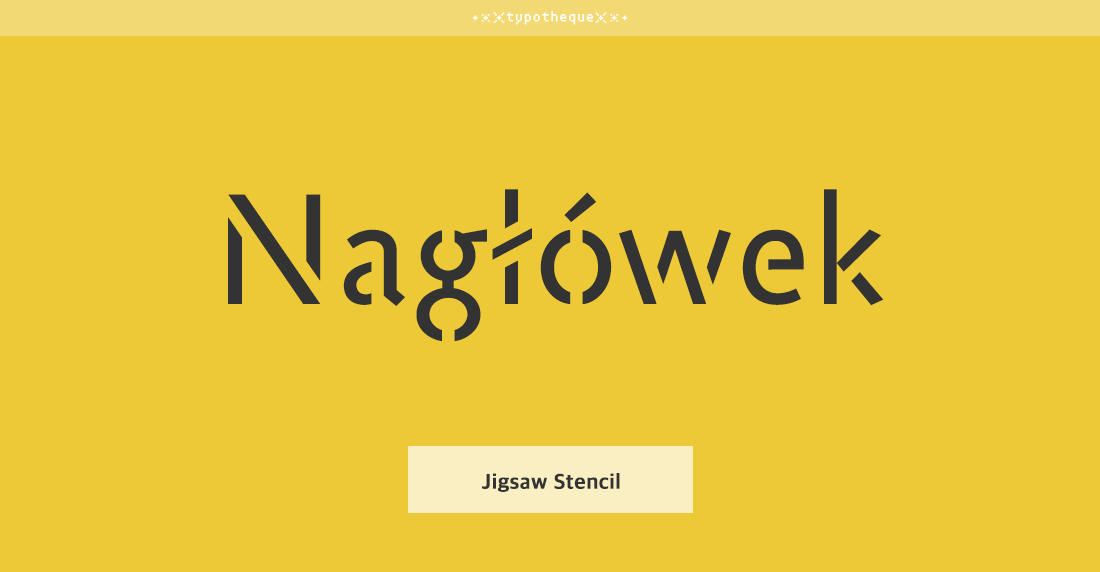
- Jigsaw Stencil Std는 수직, 수평 획의 굵기가 일정한 기하학적인 구조의 산 세리프 폰트이다.
베이직한 Jigsaw의 골격이 매우 자연스럽게 Stencil버전으로 변환되어 어색함이 없고 스텐실 특유의 개성이 느껴진다.
폰트 정보 구분 명조 디자인디렉팅 Johanna Biľak 출시년도 2008